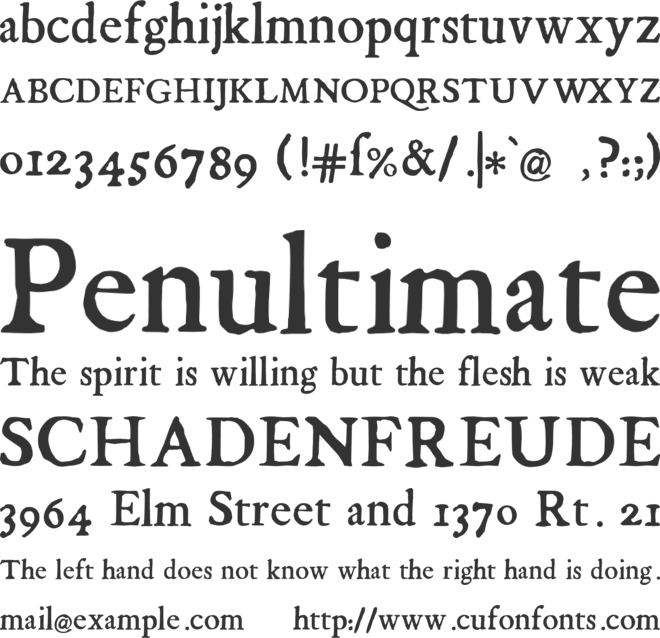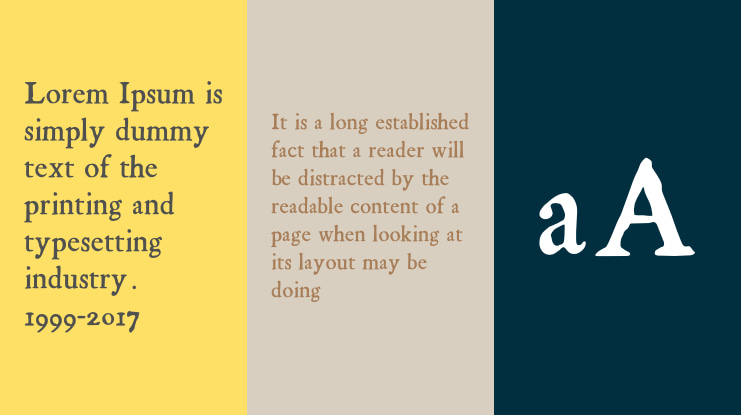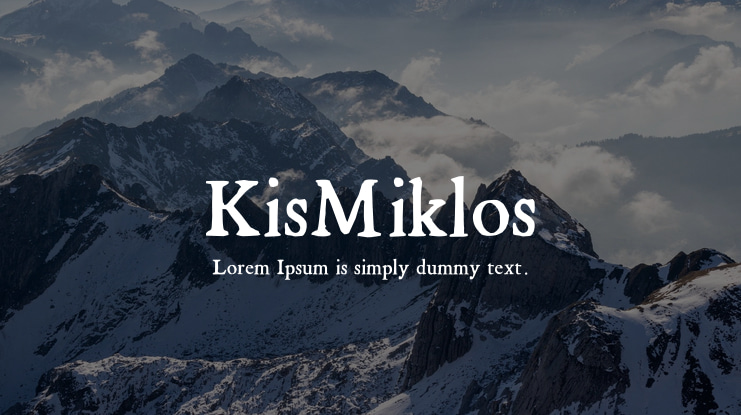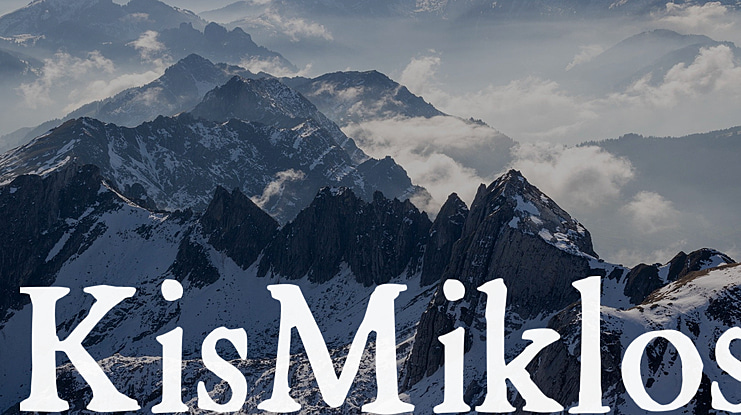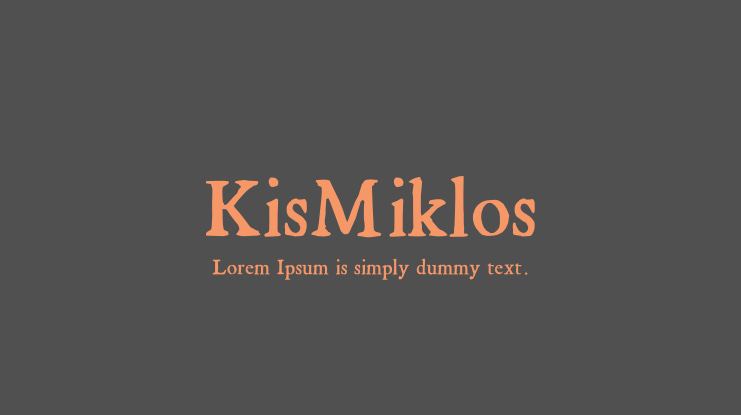
KisMiklos Font
A híres erdélyi tipográfus, Tótfalusi Kis Miklós által tervezet betűkészlet számítógépes rekonstrukciója.
Az újratervezett betű nyomdailag igényes, PostScript rajzolatú OpenType betűformátumú lett. Ligatúrákat, régies karaktereket, Tótfalusi könyveiben található ornamenseket és előre beállítot alávágást, egalizálást
is tartalmaz.